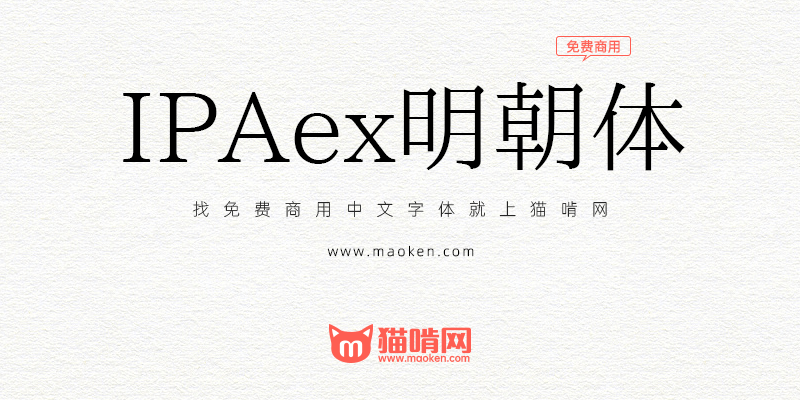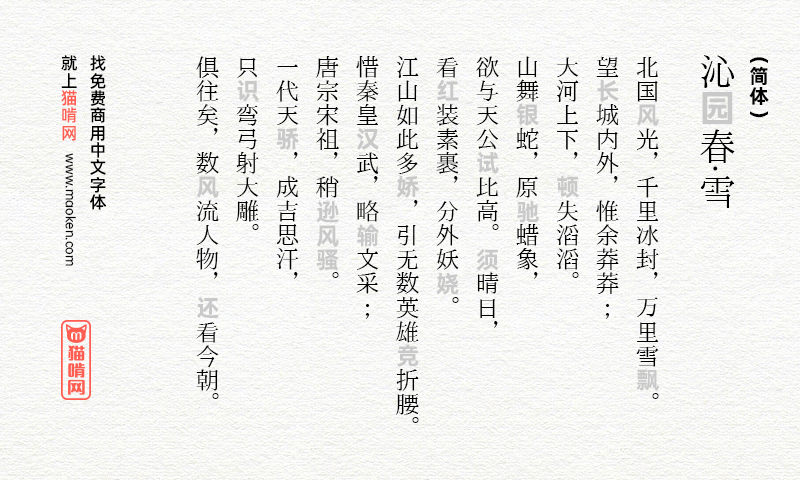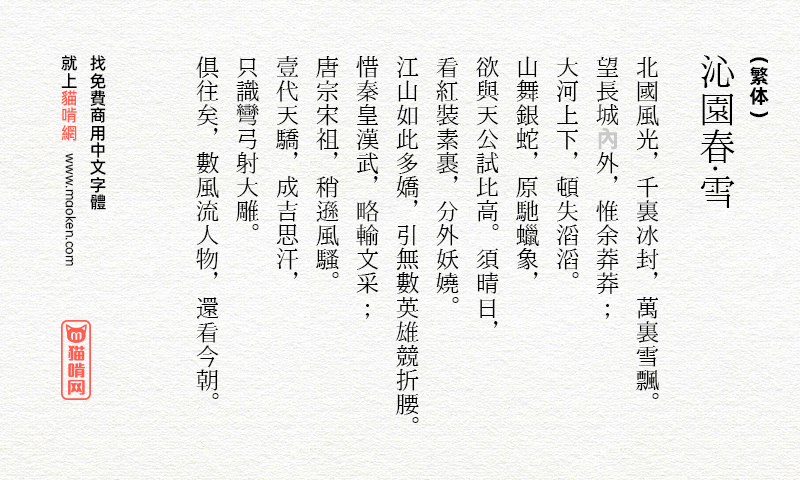
IPAex明朝体:一套中规中矩的日系宋体字型
字体作者:IPA (其他语种) 字体字重:1个
IPA从2003年开始提供“IPAFont*”系列,IPA拥有该系列的所有权利,并于2010年2月发布了“IPAex Mincho”和“ IPAex黑体 ”。IPA字体是日本OpenType字体,JIS X 0213:2004兼容,由日本信息技术促进机构提供。这种字体是基于哥特式(无衬线)风格,并包含比例拉丁文和固定宽度的日文字体。
想知道有没有基于这个字体的中文字体啊…( ´_っ`)
• 有的。包括但不限于:一點明體、霞鹜新致宋……
• 霞鹜新致宋是我留言几年后才出的哈哈,一點明體虽然类似,但是字形很多和简体字有差异